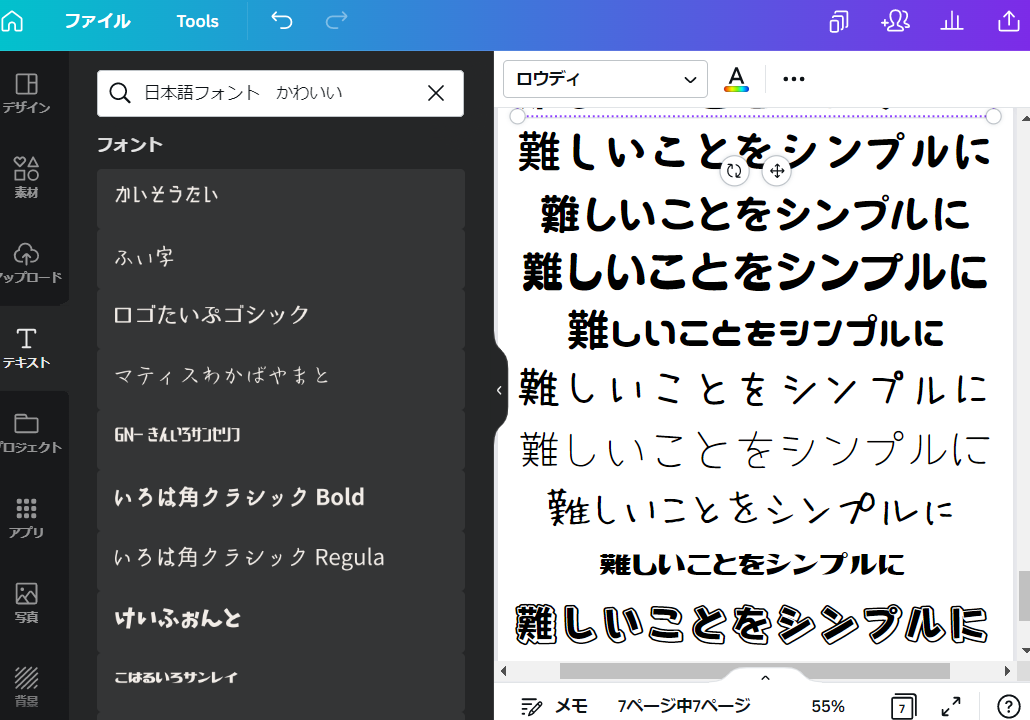
Canvaの日本語フォントは増え続けています。どんなスタイルのデザインにも合うように、バリエーション豊かに取り揃えています。日本語フォントを使えば、かわいいデザイン作成にも困ることはありません。手書きフォント、太字、ポップ文字、ブラシ、レトロ、ビンテージなど、多種類の日本語フォントでかわいい投稿や動画、チラシ、ポスター、寄せ書き、アルバムまで作れちゃいます!
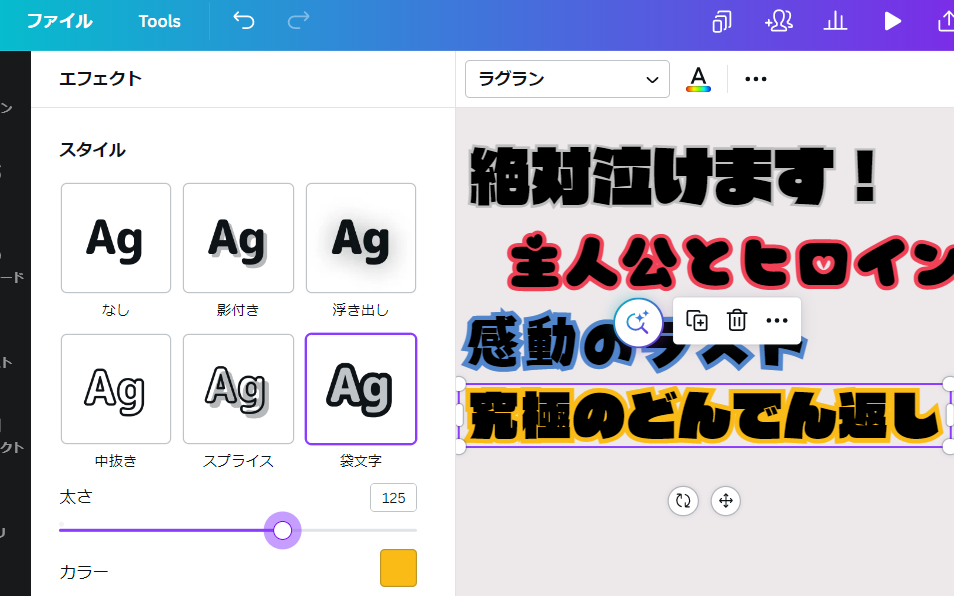
なんと、Canvaの日本語フォントに「袋文字」が加わりました!ポップ文字のような店頭で見かけるフォントデザインをお使いいただけます。上部のフォント検索ボックスから、丸みのあるかわいい日本語フォントを選択し、上部の3点線のアイコンからエフェクトで「袋文字」を選択するだけであっという間に完成!POP広告や値札、チラシに使用できる無料テンプレートもCanvaでご用意しています。用途に合わせて、かわいい日本語フォントをぜひお使いください。
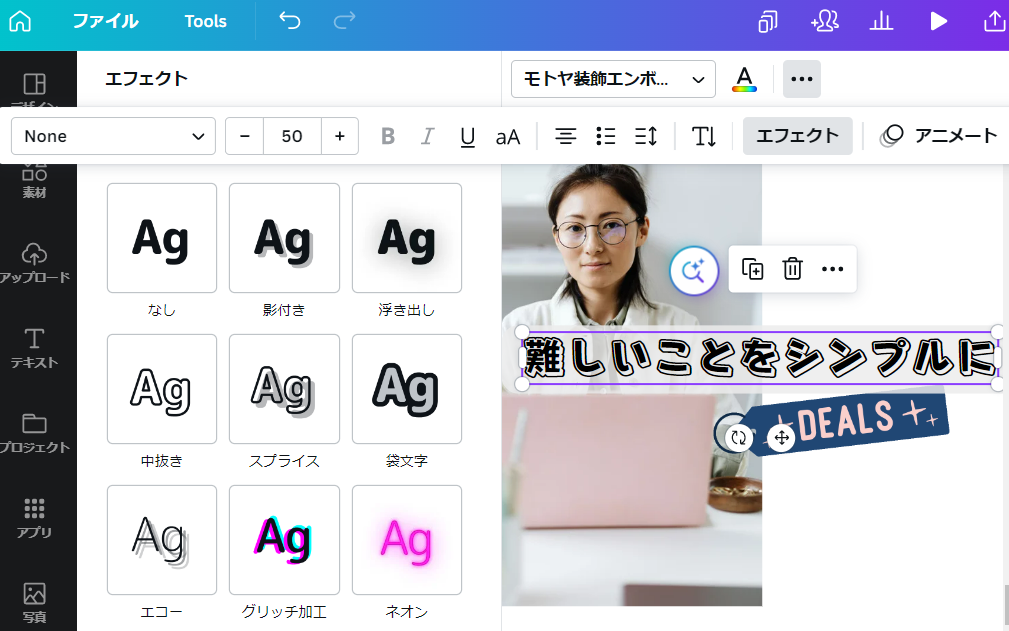
かわいい日本語フォントを選んだら、文字を入力します。テキストの色を編集するときは、上部の色アイコンをクリック。左パネルにカラーパレットが表示されるので、好きな色を選びましょう。また、文字にエフェクトを加えて引き立たたせることも可能!日本語フォントなら、影付き、浮き出し、中抜き、袋文字、ネオン、背景などが使えて、一瞬でかわいいテキストデザインに生まれ変わります。
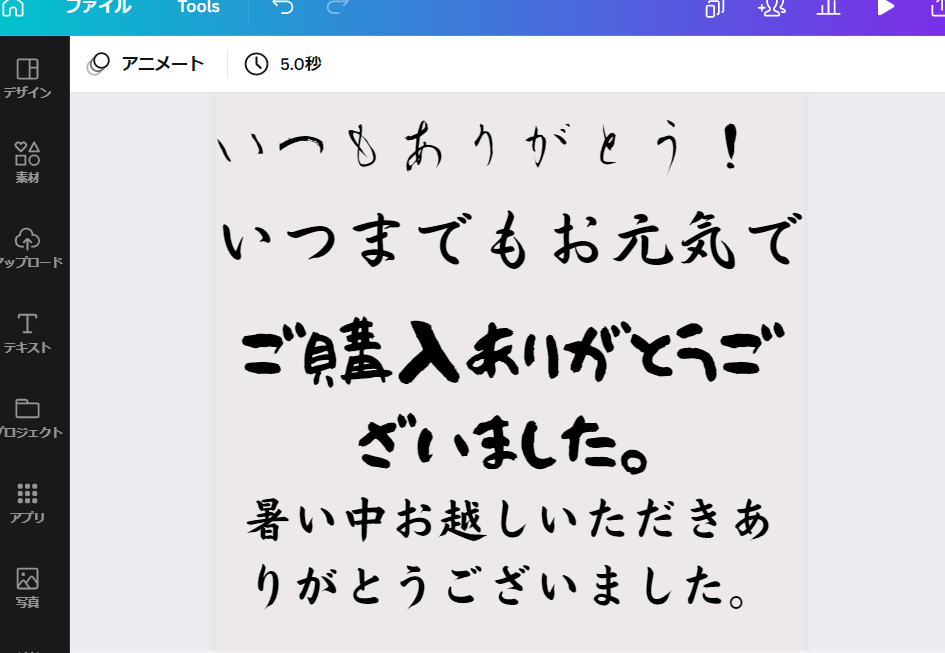
日本語フォントにもかわいいデザインも多いのですが、毛筆フォントもおすすめです。文字を上品に落ち着いた印象にさせます。ハガキやお中元、感謝状、夏のインスタ広告や和風イベントの告知デザインなど、あらゆるシーンでお使いいただけます。使い方は、[テキスト]の検索ボックスに「筆」と入力して、一覧表示された筆フォントを選ぶだけ!かわいい日本語フォントでデザインを作ったあとは、スタイリッシュでフォーマルなデザインにチャレンジしてみてください。